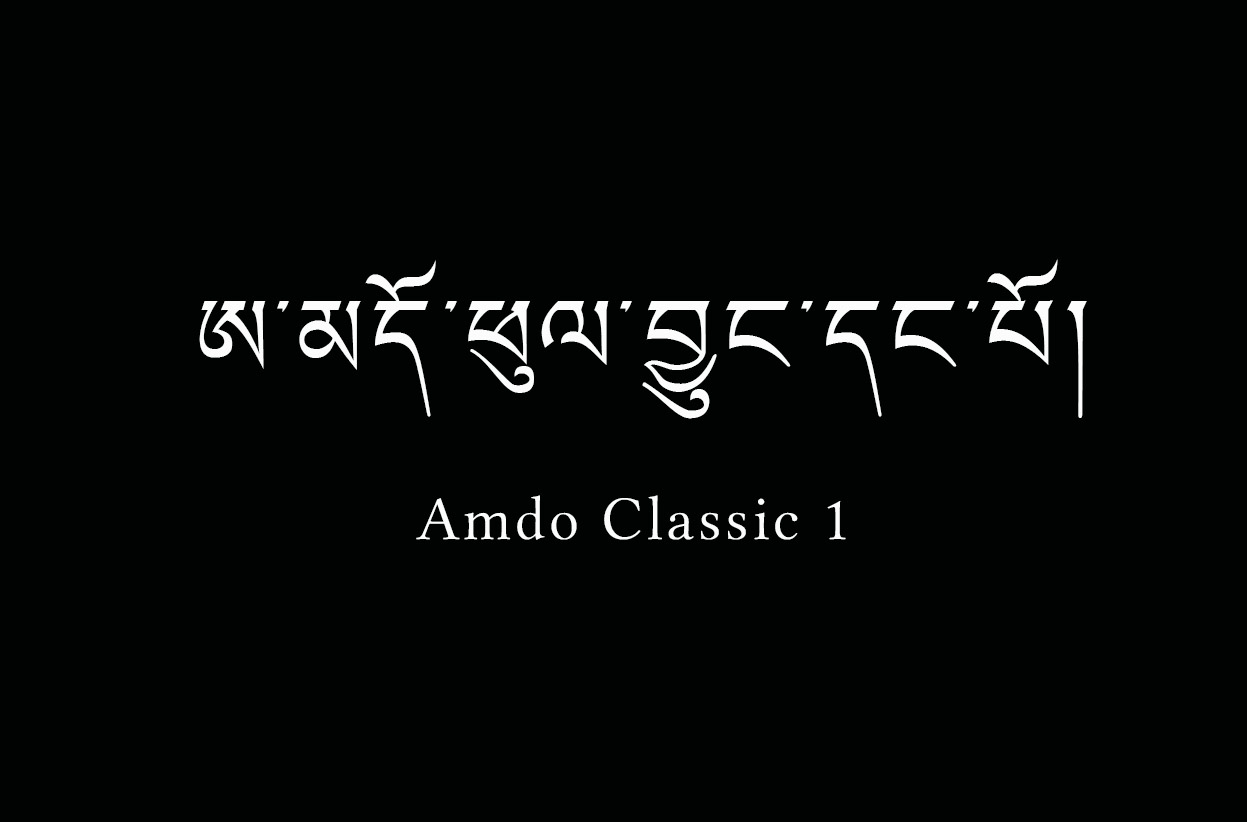
ཚད་གཞི།: རྒྱལ་སྤྱིའི་ཚད་ལྡན།
སྤེལ་དུས།: 2008
རིགས།: སྲོལ་རྒྱུན་དབུ་ཅན།
བསྲེས་སྒྲིག: ཡིག་རིགས་ཚང་མ་འདུས།
སྤྱོད་ཡུལ།: གཞུང་ཡིག་དང་བརྡ་སྦྱོར། སློབ་གསོ།
ཇུས་བཀོད་པ།: མཚོ་སྔོན་མི་རིགས་སློབ་ཆེན།
འདིར། ཨ་མདོ་ཕུལ་བྱུང་ ༡ དང་ ཨ་མདོ་ཕུལ་བྱུང་ ༣ ཡོད་པར་བལྟས་ན། ཨ་མདོ་ཕུལ་བྱུང་ ༢ ཟེར་བ་ཞིག་ཡོད་པ་འདྲ། འོན་ཀྱང་ཨ་མདོ་ཕུལ་བྱུང་ ༢ དེ་ལག་སོན་མ་བྱུང་།